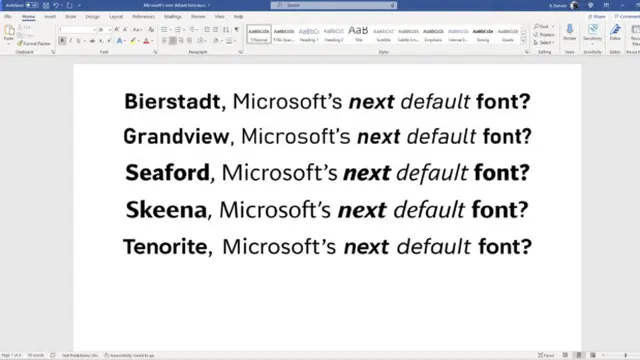
Liputan6.com, Jakarta - Microsoft mengumumkan akan melepas Calibri dari font default (bawaan) Microsoft Office. Setelah debutnya sejak 2007, Calibri akan menyusul Clippy dan Internet Explore yang lebih dulu meninggalkan Windows.
"Calibri telah menjadi font default untuk semua hal Microsoft sejak 2007, ketika ia menggantikan Times New Roman di Microsoft Office," kata tim Desain Microsoft, seperti dikutip dari Ars Technica, Jumat (30/4/2021).
Menanggapi hal ini, Microsoft kini mencari pengganti Calibri untuk menempati posisi font default di sistemnya.
Alih-alih membuka pencarian ke font tulisan yang terdahulu, perusahaan telah memutuskan lima jenis font untuk bersaing.
Di antaranya adalah Tenorite, Bierstadt, Skeena, Seaford, dan Grandview. Kelimanya termasuk dalam model sans serif, yang telah dibocorkan oleh tim desain Microsoft.
Font Pengganti
Pilihan pertama, Tenorite tampaknya menjadi pembanding berlawanan dari Calibri, dengan struktur bulat, lebar, dan tajam dengan sudut yang lebih lembut dan proporsi sempit.
Selanjutnya, Bierstadt merupakan jenis baru dari kategori ‘grotesque sans serif’.
Kemudian, Skeena dan Seaford berbasis sans serif yang masing-masing memiliki aspek serif tertentu.
Skeena, berdasar pada tipografi serif, dan Seaford berlandaskan pada desain serif gaya lama.
"Untuk menunjukkan dengan tepat jenis keakraban dan 'kenyamanan' yang harus ditimbulkan oleh jenis huruf tersebut, kami juga melihat gambar kursi berlengan lama: dalam istilah kursi, kami mencari interpretasi praktis dari pusaka keluarga yang indah; kain pelapis yang tahan lama, tidak ada yang terlalu mewah atau bernostalgia," tulis desainer Nina Stössinger.
Terinspirasi dari Rambu Jalan
Sementara untuk Grandview, sang desainer Aaron Bell menyebut ia terinspirasi dari rambu jalan dan kereta api Jerman klasik yang mudah dikenali meski dari jarak jauh dan cuaca gelap.
Atas dasar itu, ia berharap font buatannya juga sesuai dengan prinsip mudah dibaca dan dipahami.
“Ini menghasilkan keterbacaan yang lebih baik pada ukuran yang lebih kecil pada resolusi rendah perangkat, yang penting karena Grandview ditujukan untuk teks tubuh di komputer mana pun yang menjalankan Windows,” tuturnya.
Rencananya, dari kelima kandidat font ini, pemenanganya akan mengantikan Calibri untuk layanan Microsoft365.